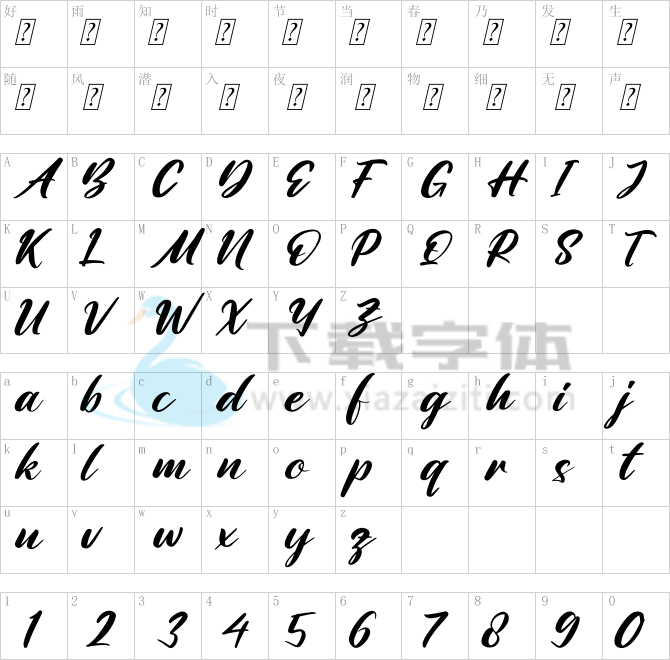
Amattera Million.ttf字体下载,这款字体结构工整、笔画清晰,兼顾美观与易读性,适用于标题、正文、海报、包装、LOGO 等多种场景。字形优雅稳定,风格百搭耐看,适配日常排版与创意设计,让文字呈现更舒适、更具质感。Amattera Million.ttf字体下载一笔一画,皆是细节,以均衡的比例、流畅的线条打造舒适视觉体验,字形端正大气,风格简约现代。无论是商业设计、品牌宣传还是日常排版,都能轻松驾驭,让文字更有格调与力量。Amattera Million.ttf字体下载字体下载。